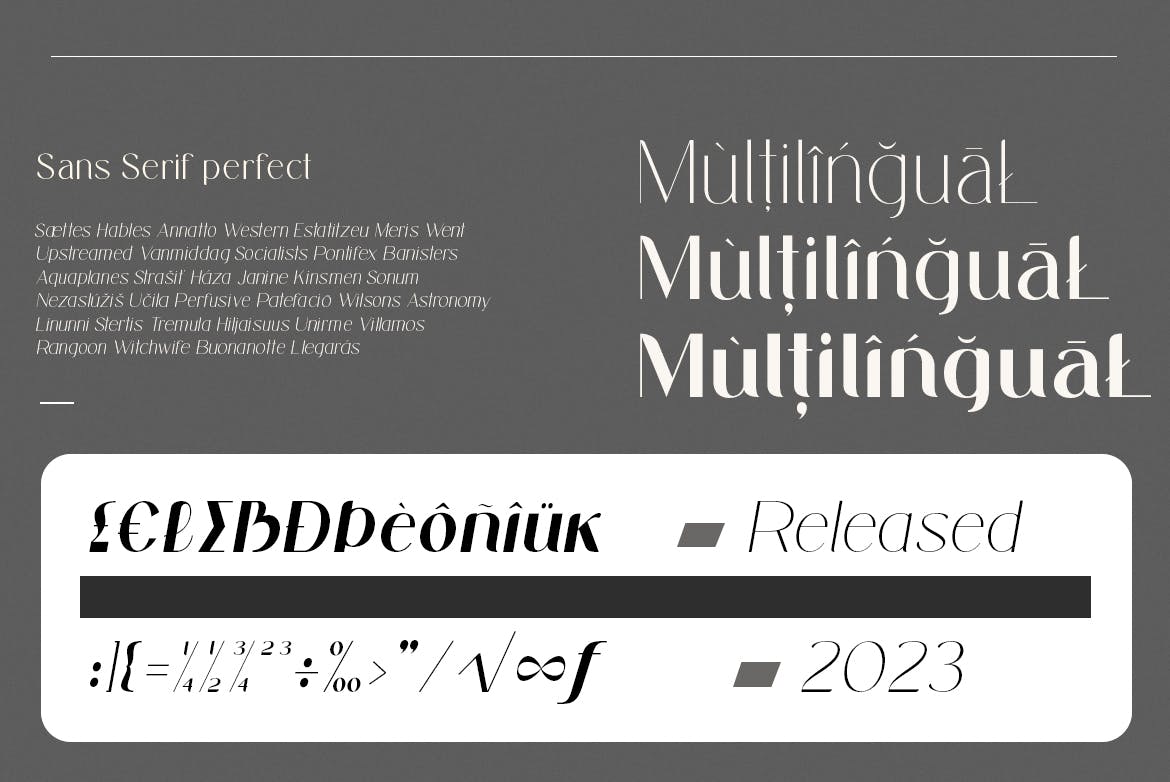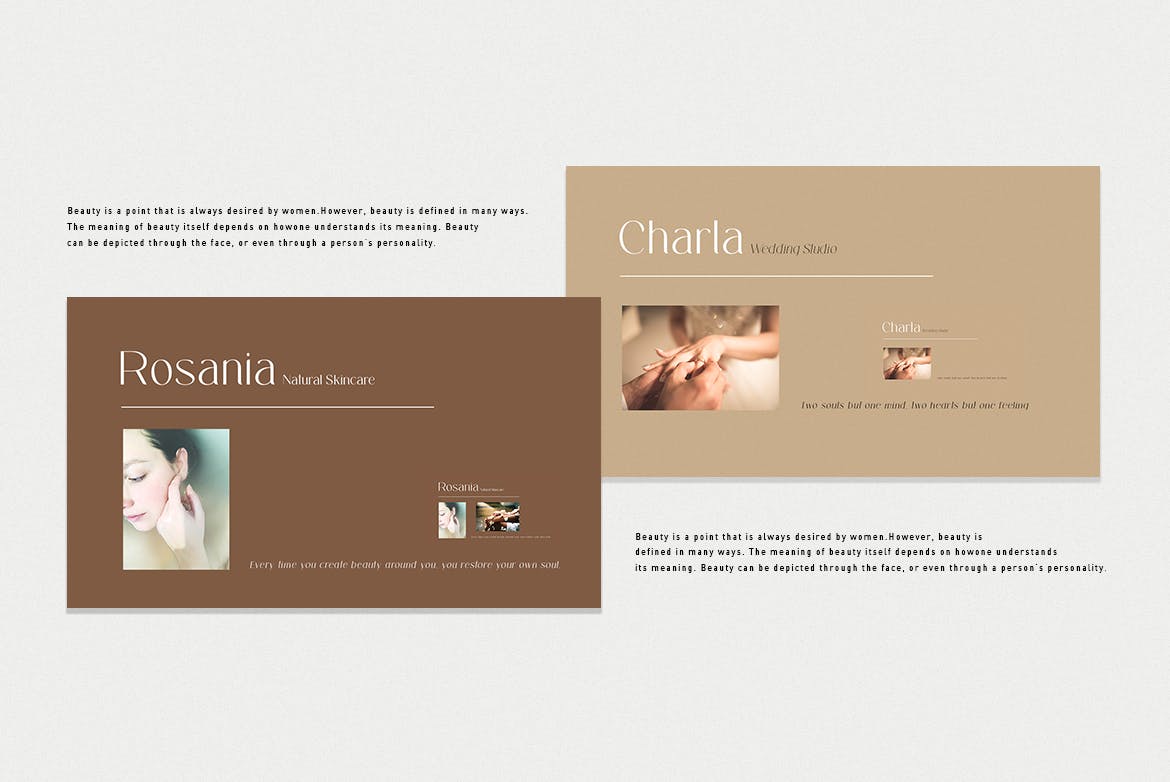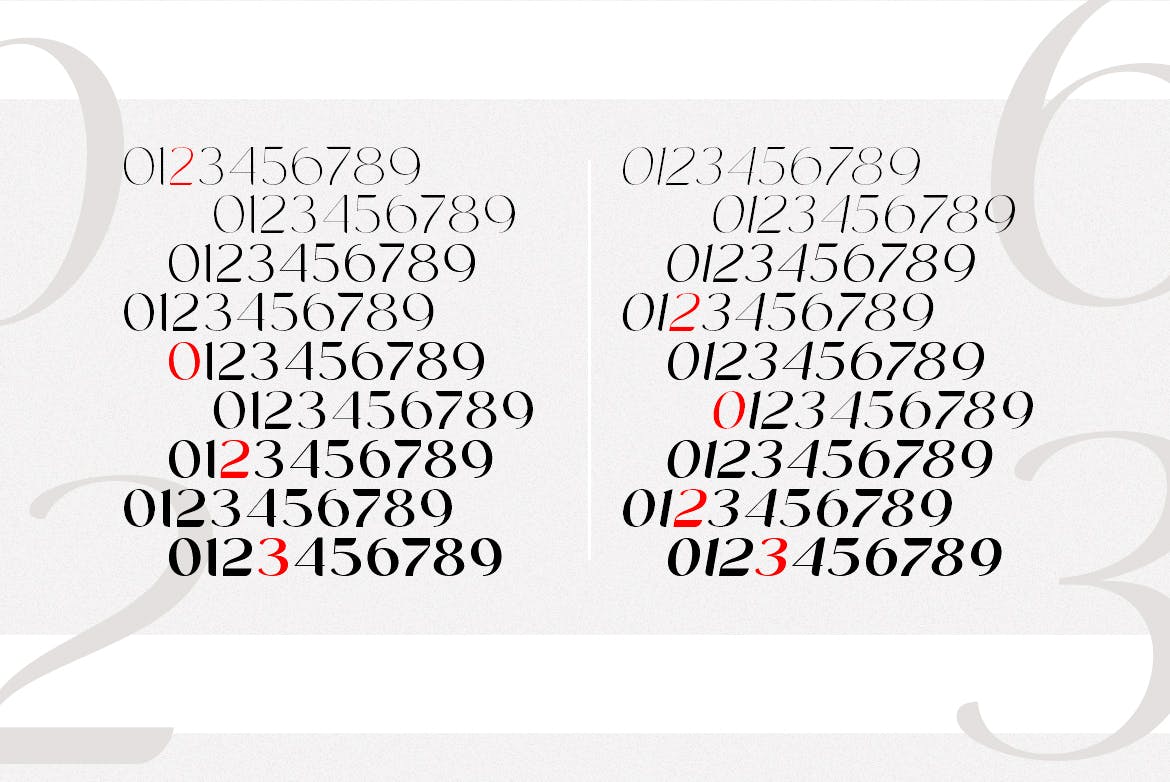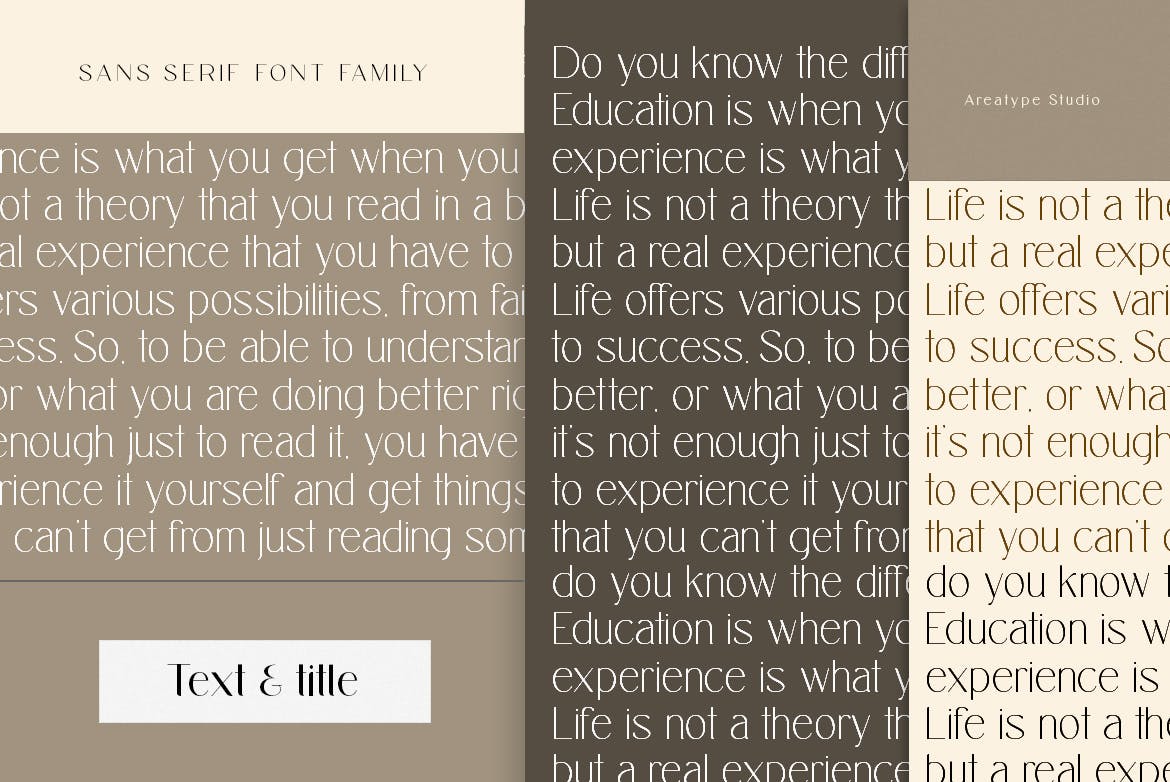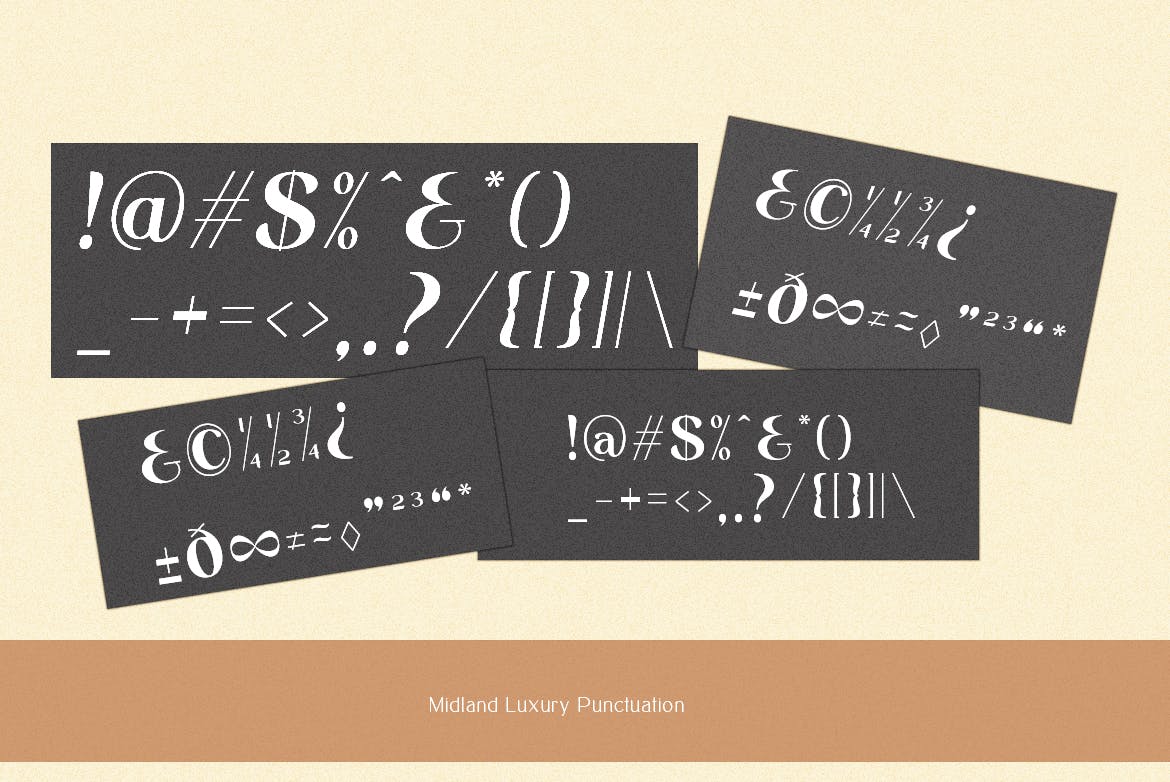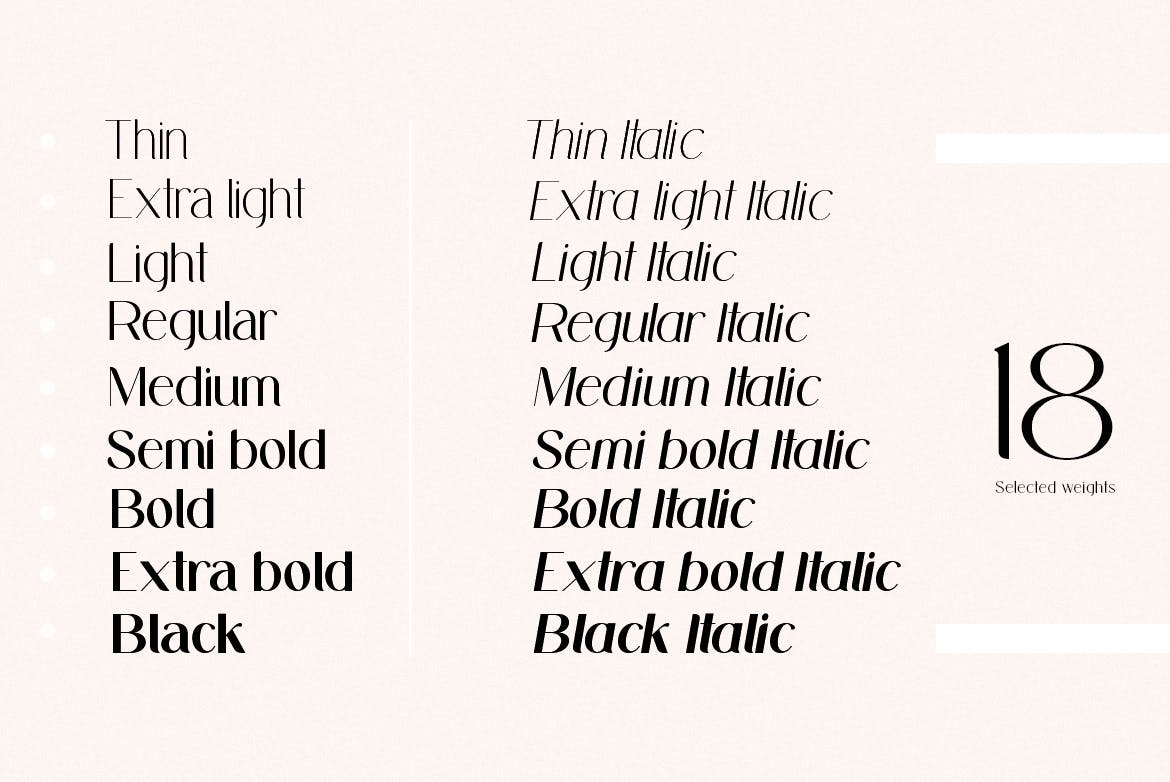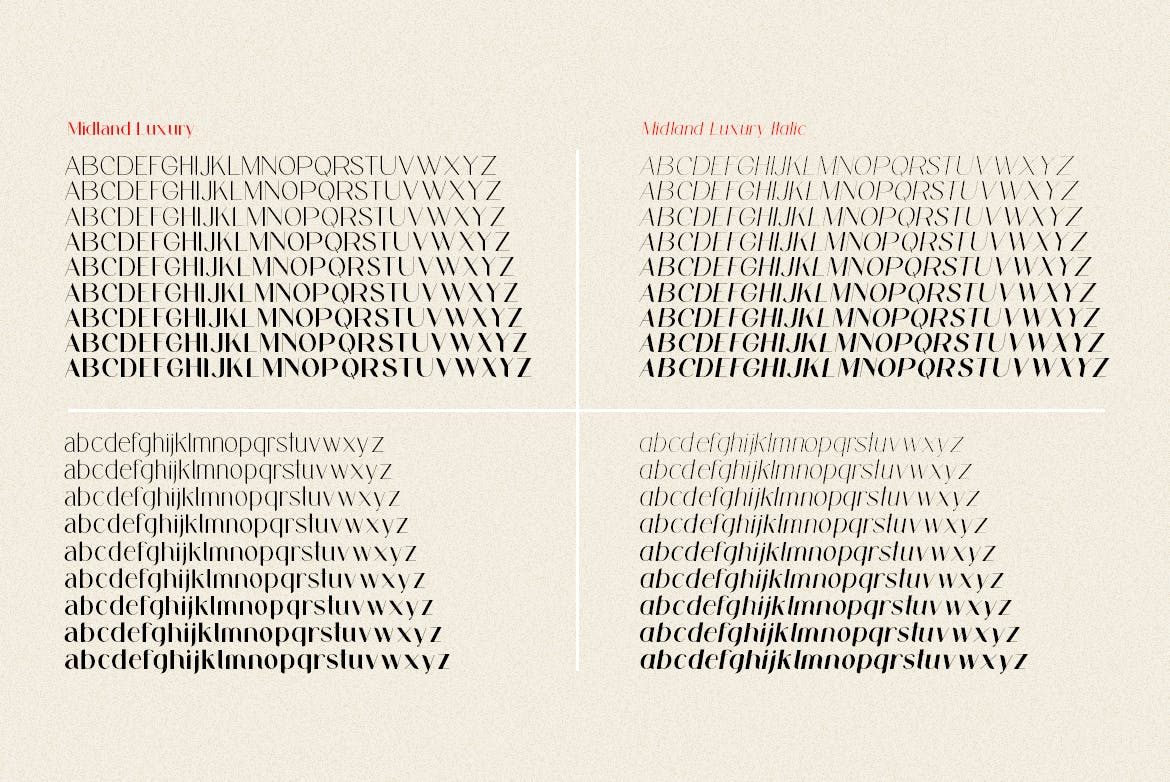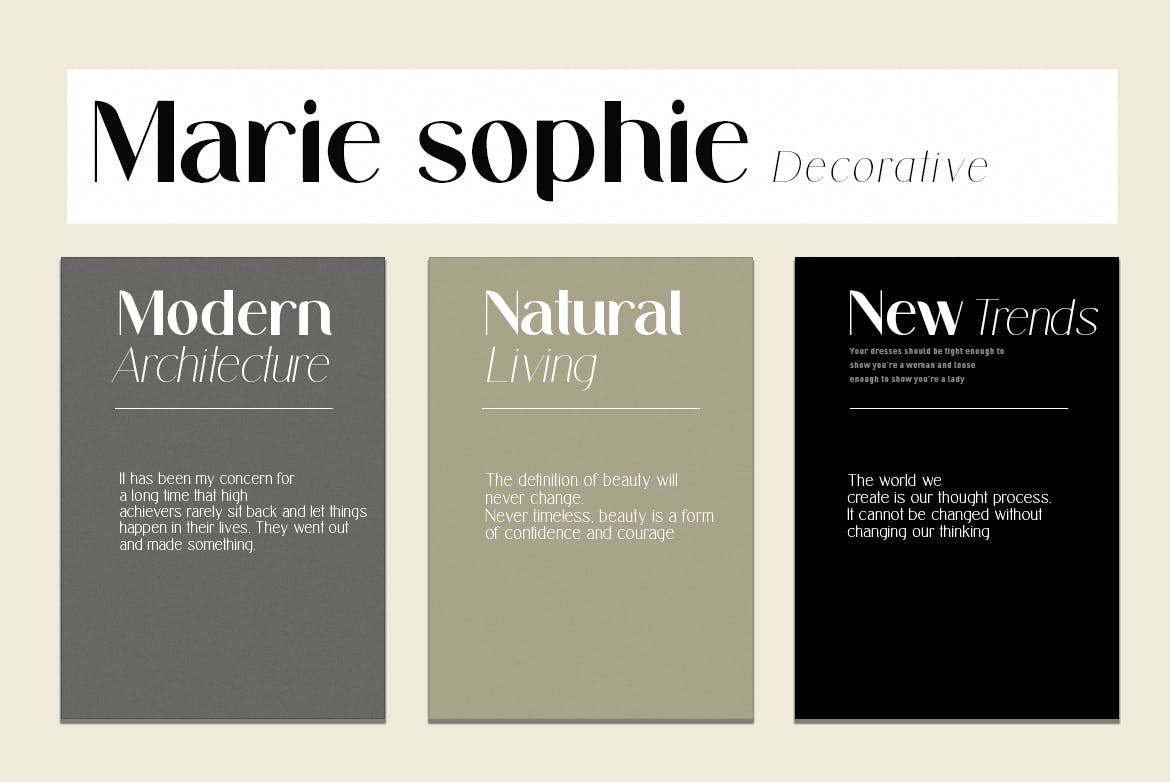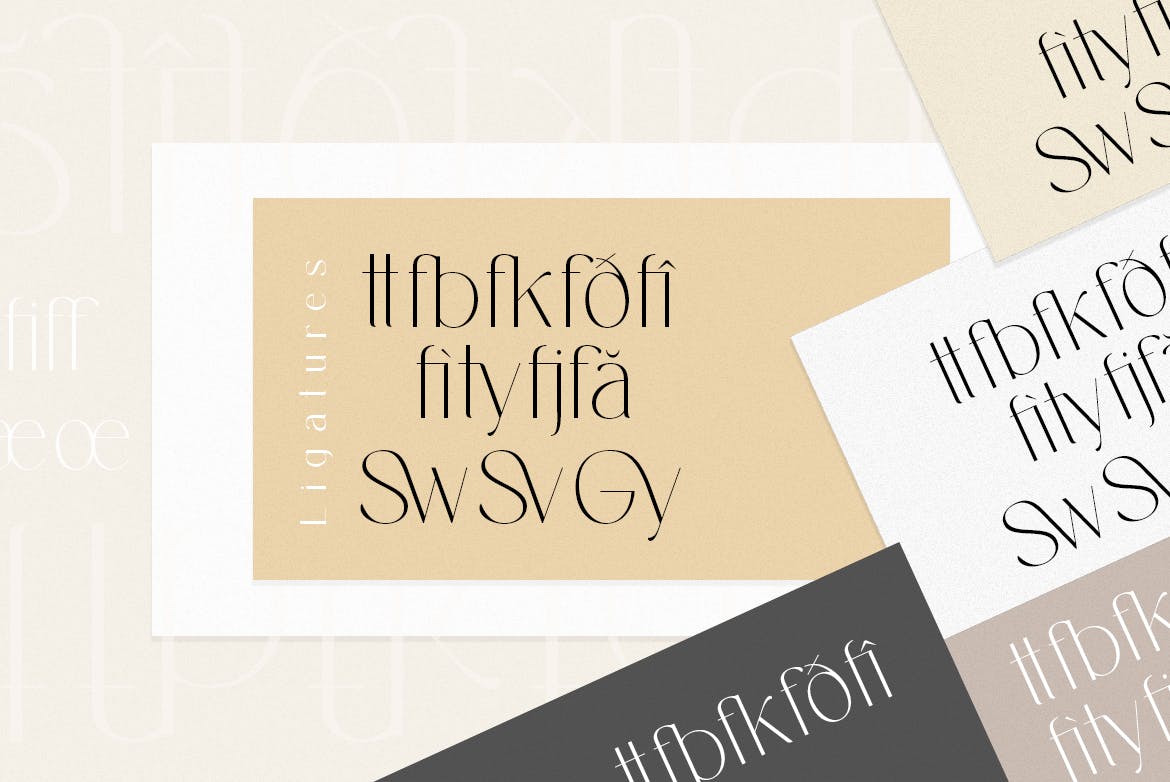
فونت میدلند لاکچری یک فونت سنس سریف بسیار متنوع است که برای طراحیهای مختلف از جمله تصاویر مجله، دعوتنامههای عروسی، برندینگ، طراحی پوستر و موارد دیگر مناسب میباشد.